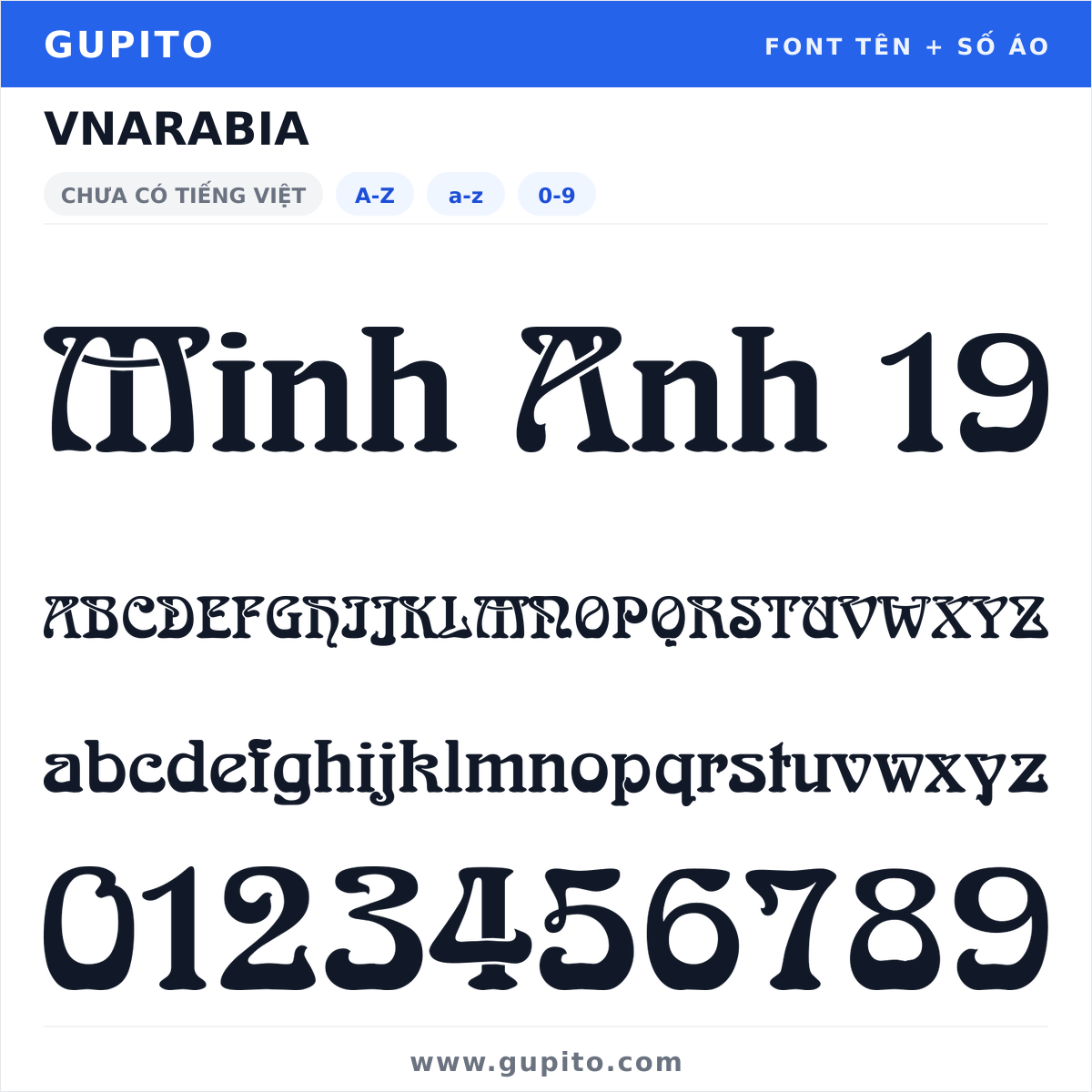
.VnArabia
.VnArabia · Font VNARABIA in tên áo, số áo bóng đá, áo lớp · chữ nghệ thuật, có chân
Font VNARABIA với nét chữ độc đáo, có bảng số 0-9, thích hợp in tên áo, số áo bóng đá, áo lớp, quà tặng. Bộ chữ .VnArabia dùng để in chuyển nhiệt lên áo đấu, áo lớp, áo nhóm và đồ thể thao theo yêu cầu. Kiểu dáng: chữ nghệ thuật, có chân. Font dùng cho chữ không dấu và số áo. Có đủ bộ chữ số để in số áo. Từ khoá liên quan: font vnarabia, font in ten ao, font in so ao, font ao bong da, font ao lop, font in chuyen nhiet, font co bang so, font chu hoa.